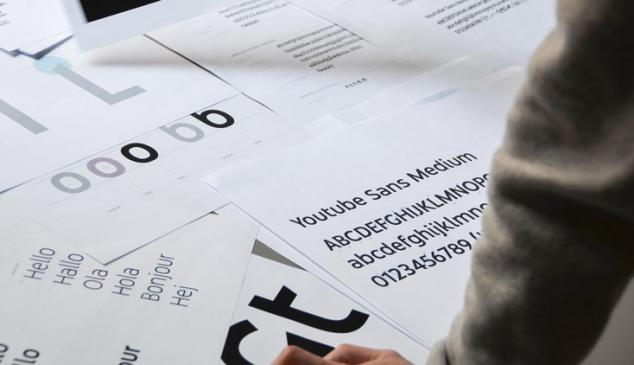
YouTube ha dado a conocer su primera tipografía propia, inspirada en el botón de play que acompaña desde hace años al logotipo de la compañía.
Bajo el nombre de YouTube Sans, la tipografía se ha diseñado de forma interna en YouTube, con el apoyo de la consultora Saffron. El objetivo era crear un tipo de letra “expresiva” al mismo tiempo que “sencilla y con fuerza”, declaran desde Saffron.
Además, el botón de play se ha rediseñado para convertirlo en un símbolo más junto a todos los que componen YouTube Sans. A partir de ahora la nueva tipografía se usará en YouTube TV así como en todos los productos y comunicaciones de marketing de la compañía.